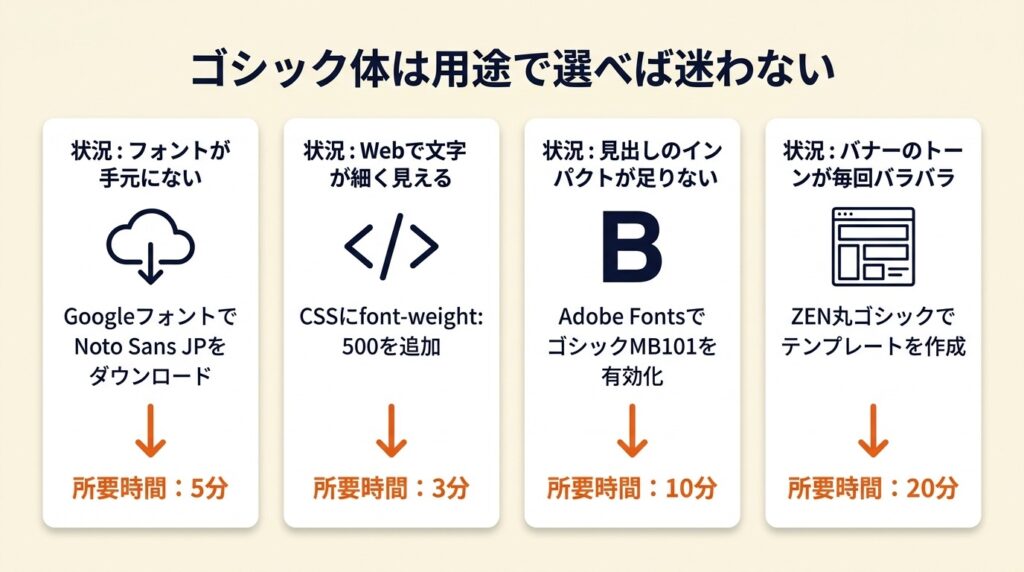
游ゴシック、Noto Sans JP、ゴシックMB101など、用途に合うゴシック体を7本に絞り込みました。無料・商用利用可・ウエイト数を軸に比較し、見出し・本文・Web・印刷それぞれの最適解を解説します。
用途・予算・ウエイト数の3軸でゴシック体を最短で選べる比較表と診断を掲載しています。無料フォントだけで9割の用途をカバーする方法、游ゴシックのWeb表示を3分で改善するCSS設定、SNSバナーの制作コストを半減するテンプレート化の手順も解説します。
ゴシック体選びは「無料か有料か」より「何に使うか」で決まります。Web・資料の本文ならNoto Sans JPを最初に試し、見出しや広告に力強さが必要なときはゴシックMB101を重ねるのが最短ルートです。柔らかい印象を出したいときはA1ゴシックまたはZEN丸ゴシックを選び、フォントウエイトで情報の階層を作れば迷いはほぼなくなります。
ゴシック体おすすめ7選は5軸で比較
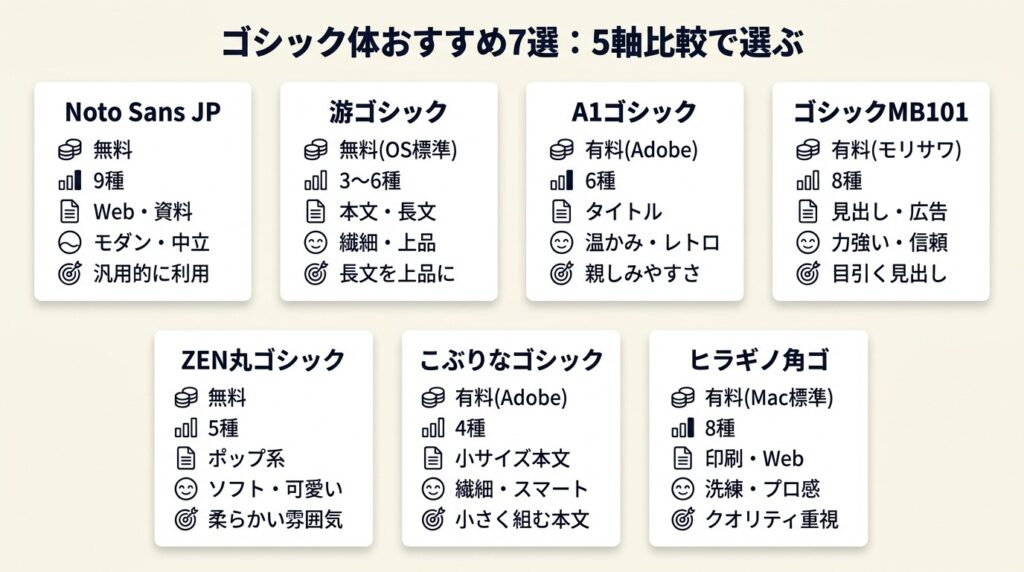
線幅が一定で「うろこ」「はね」「はらい」がないゴシック体は、明朝体よりポップさや力強さを出しやすい反面、フォントごとの個性の差がわかりにくいという特徴があります。以下の5軸で7本を比較すると、選択の根拠が明確になります。
| フォント名 | 価格 | ウエイト数 | 主な用途 | 印象 | 向いているケース |
| Noto Sans JP | 無料 | 9 | Web・資料・本文 | モダン・中立 | とにかく汎用的に使いたい |
| 游ゴシック | 無料(OS標準) | 3〜6 | 本文・長文 | 繊細・上品 | 長文を上品に見せたい |
| A1ゴシック | 有料(Adobe Fonts) | 6 | タイトル・柔らか印象 | 温かみ・レトロ | 親しみやすさを出したい |
| ゴシックMB101 | 有料(モリサワ) | 8 | 見出し・広告 | 力強い・信頼感 | 目を引く見出しが必要 |
| ZEN丸ゴシック | 無料 | 5 | ポップ・ナチュラル系 | ソフト・可愛らしい | 柔らかい雰囲気のデザイン |
| こぶりなゴシック | 有料(Adobe Fonts) | 4 | 小サイズ本文 | 繊細・スマート | 本文を小さく詰めて組む |
| ヒラギノ角ゴ | 有料(Mac標準付属) | 8 | 高品質印刷・Web | 洗練・プロ感 | 印刷物でクオリティを上げたい |
Noto Sans JPは9ウエイトで階層化が最も効率的
Noto Sans JPはGoogleとAdobeが共同開発したフォントで、視認性・可読性・判読性のすべてで高い評価を受けています(Adobe フォント解説)。9段階のウエイトを持ち、H1見出しにはWeight 700、本文にはWeight 400、注釈にはWeight 300と使い分けるだけで情報の階層が視覚的に整理できます。1フォントだけで資料全体のタイポグラフィが完結するため、複数フォントを組み合わせるスキルがまだ身についていない段階でも実質的なリスクがゼロです。
「視認性、可読性、判読性の全てが高いゴシック体フォント」「素朴で優しい字形をした美しいフォント」という評価があります(おすすめフォント – 伝わるデザイン)。フォントの選び方に迷ったときは、日本語フォント無料おすすめ12選も参考になります。
游ゴシックは小サイズでも文字がつぶれない
游ゴシックはWindowsとMac双方にOS標準搭載されており(Macは一部バージョンで追加インストールが必要)、追加費用なく使い始められる点が最大の実用メリットです。線が繊細で字間が均等に整っているため、10pt以下の小さなサイズで組んでも文字がつぶれにくい構造になっています。
「けっこう好き嫌いが分かれるようですが、繊細で上品なところが特長のフォントです」という評価があります(歴15年デザイナーのフォント解説)。
Windows環境では游ゴシックをブラウザ本文に指定した場合にウエイトが細すぎて読みにくくなるケースがあります。font-weightを500または700に上げるCSSを追加するだけで解消できます。
A1ゴシックの墨だまりは温かみを視認段階で伝える
A1ゴシックはモリサワが提供するオールドスタイルのゴシック体で、文字の角に「墨だまり」と呼ばれる丸みが付いています。この墨だまりが、同じ文字組みでも「機械的」ではなく「手が加わった」印象を視認段階で与える効果があります(モリサワ作例・使い分け解説)。食品・福祉・教育系のデザインで感情的な親しみやすさを求める場面では、Noto Sans JPよりA1ゴシックを優先的に検討してください。IT系・金融系・官公庁向けのデザインでは温かみが「雑然とした印象」に転じることがあるため、業種との相性を確認してください。
Q: ゴシック体と明朝体はどう使い分けますか?
A: ゴシック体は線幅が均一で視認性が高いため、画面表示・見出し・短いキャッチコピーに向いています。明朝体は長文の印刷物で読み進めやすさを高める場合に使います。同じ資料でも見出しをゴシック体、本文を明朝体にするだけで可読性が上がります。
Q: ウエイトとは何ですか?
A: ウエイトとは文字の太さの段階を指します。Noto Sans JPであればWeight 100(最細)からWeight 900(最太)まで9段階あり、数字が大きいほど太くなります。同じフォントのウエイト違いを使い分けるだけで、異なるフォントを混在させずに情報の重要度を視覚化できます。
ゴシック体は用途で選ぶ3分診断
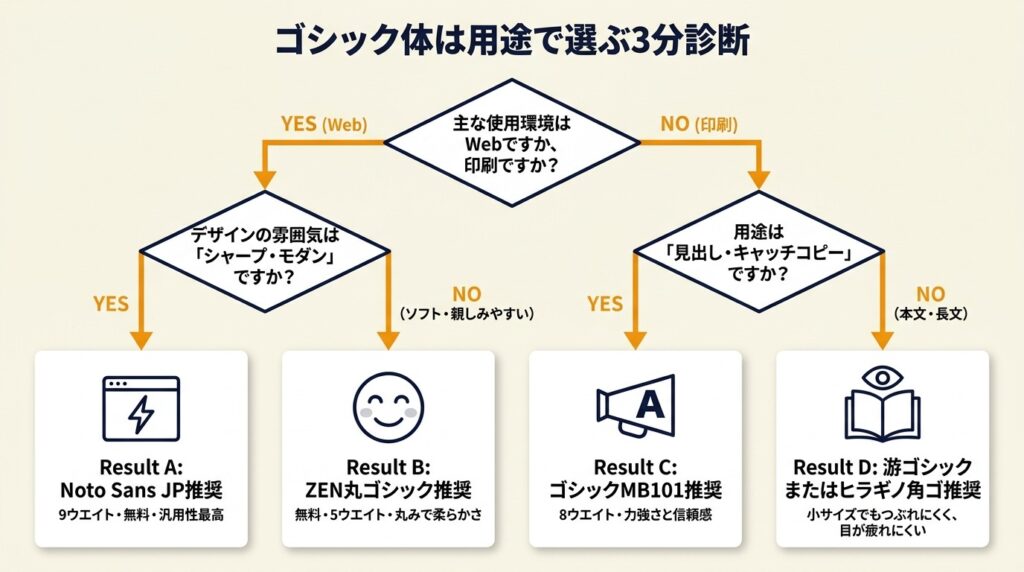
以下の質問に答えるだけで3分以内に最適なゴシック体を絞り込めます。
Q1: 主な使用環境はWebですか、印刷ですか?
Webが主ならQ2へ進んでください。印刷が主ならQ3へ進んでください。
Q2: デザインの雰囲気は「シャープ・モダン」ですか、「ソフト・親しみやすい」ですか?
シャープ・モダンなら**Result A: Noto Sans JP推奨(9ウエイト・無料・汎用性最高)です。ソフト・親しみやすいならResult B: ZEN丸ゴシック推奨**(無料・5ウエイト・丸みで柔らかさを演出)です。
Q3: 用途は「見出し・キャッチコピー」ですか、「本文・長文」ですか?
見出し・キャッチコピーなら**Result C: ゴシックMB101推奨(8ウエイト・力強さと信頼感を両立)です。本文・長文ならResult D: 游ゴシックまたはヒラギノ角ゴ推奨**(小サイズでもつぶれにくく、長時間読んでも目が疲れにくい)です。
Result B**: ZEN丸ゴシックもGoogleフォントで配布中です。ウエイト5段階あり、子ども向け・食品系・ライフスタイル系に特に相性が良いフォントです。
Q: 結果Aと結果Bを一つの制作物で混在させてもいいですか?
A: 1制作物で使うフォントは2書体以内に抑えることが推奨されています。Noto Sans JPとZEN丸ゴシックは印象が異なるため、タイトルと本文で役割を明確に分けた上で使うか、どちらか一方に統一するとビジュアルのまとまりが生まれます。
Q: 診断外のフォントを選んでも問題ありませんか?
A: 問題ありません。診断はあくまで出発点です。実際には複数フォントを並べてビジュアル確認した上で決定することが最も確実です。
ゴシック体の実例は2パターンで比較
ゴシック体選びで失敗する人と成功する人の差は、フォントのスペックではなく、用途との適合性を事前に確認したかどうかにあります。
ケース1(成功パターン): 資料制作でNoto Sans JPをウエイト階層化した事例
フリーランスのWebデザイナーが提案資料を作成する際、従来は複数フォントを混在させて「まとまりがない」と指摘を受けていました。Noto Sans JPのみを使い、H1にWeight 700、小見出しにWeight 500、本文にWeight 400を割り当てたところ、クライアントから「読みやすくプロフェッショナルに見える」と評価が変わりました。フォントを減らしてウエイトで代替することで、一貫したトーンを維持したまま情報の重要度が視覚化された事例です。
「視認性、可読性、判読性の全てが高いゴシック体フォント」「素朴で優しい字形をした美しいフォント」という評価があります(おすすめフォント – 伝わるデザイン)。無料文字フォントの活用法も合わせて確認しておくと、フォント選定の幅が広がります。
Q: ゴシック体と明朝体、どちらを選ぶべきですか?
A: 画面表示が主な用途であればゴシック体を優先してください。明朝体の細い線は低解像度モニターでジャギーが目立ちやすく、長時間読むと疲れやすくなります。印刷物の長文本体(書籍・パンフレット本文など)では明朝体の方が読み進めやすいという評価が一般的です。
Q: Windows/Macで同じフォントが表示されない場合の対策は?
A: 最も確実な対策はNoto Sans JPのようなWebフォントをCSS @font-faceで読み込む方法です。GoogleフォントのNoto Sans JPはCDN経由でWebフォントとして配信されており、OS・ブラウザ間の表示差を大幅に低減できます(Google Fonts – Noto Sans JP)。